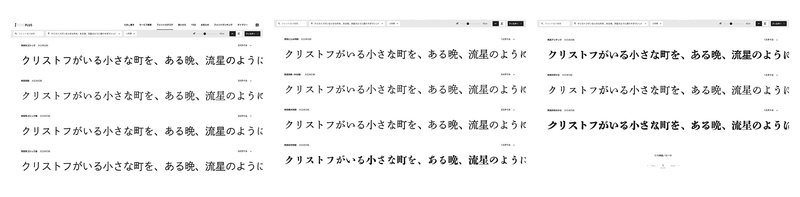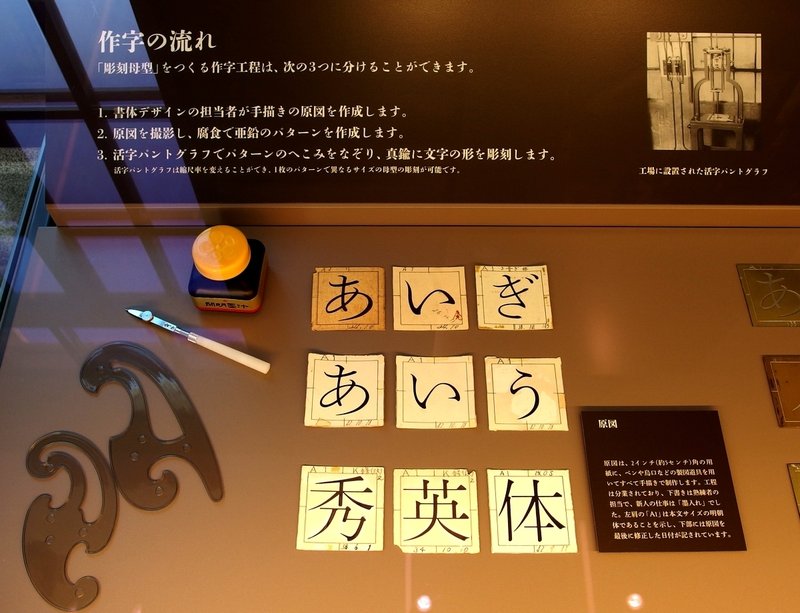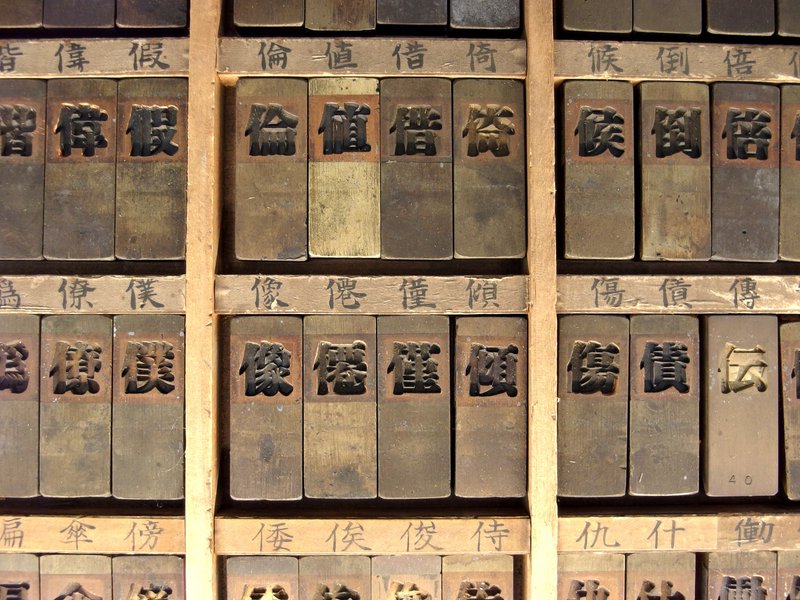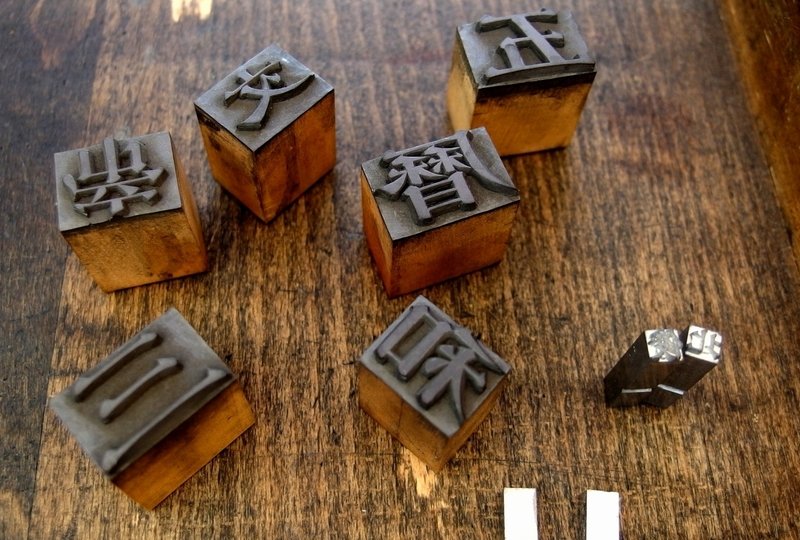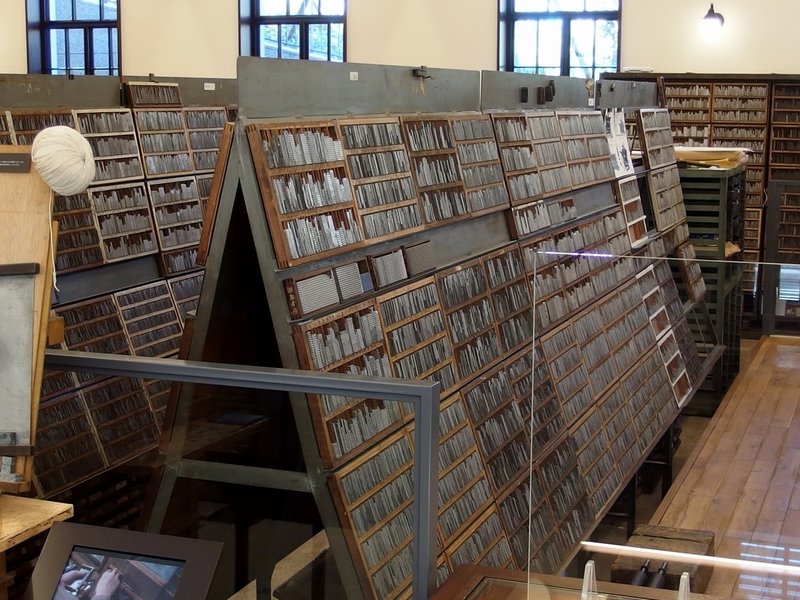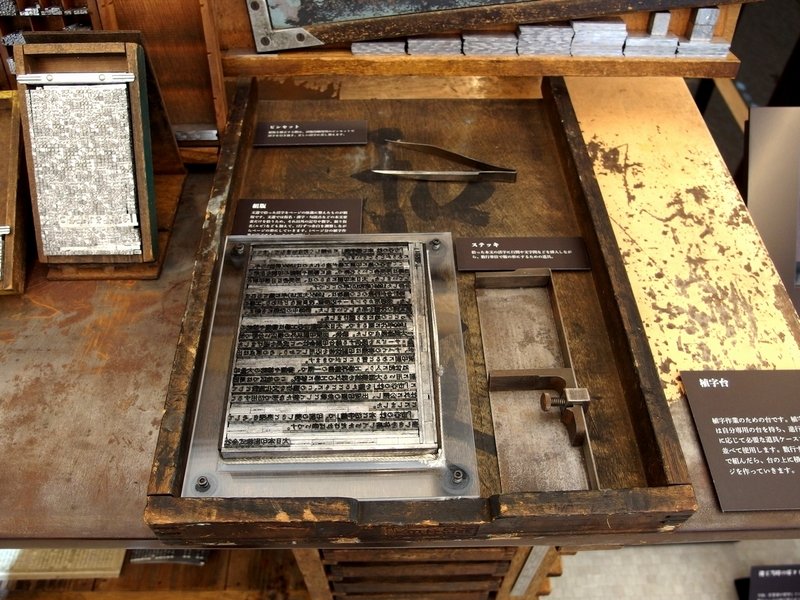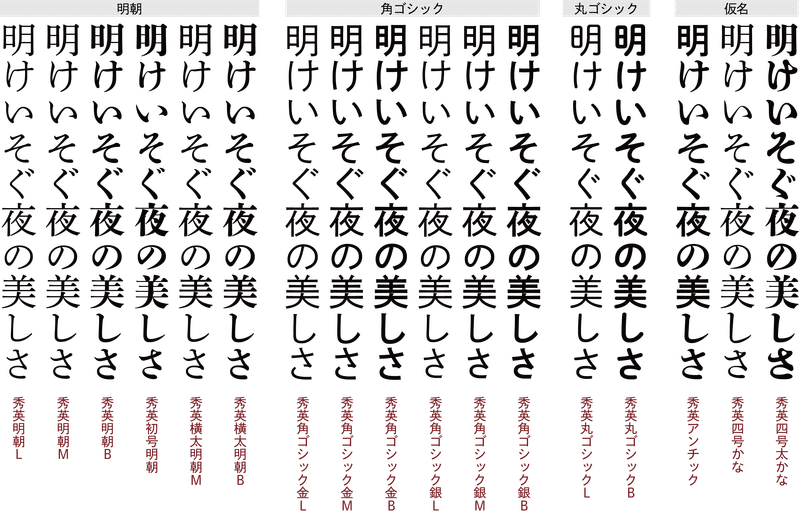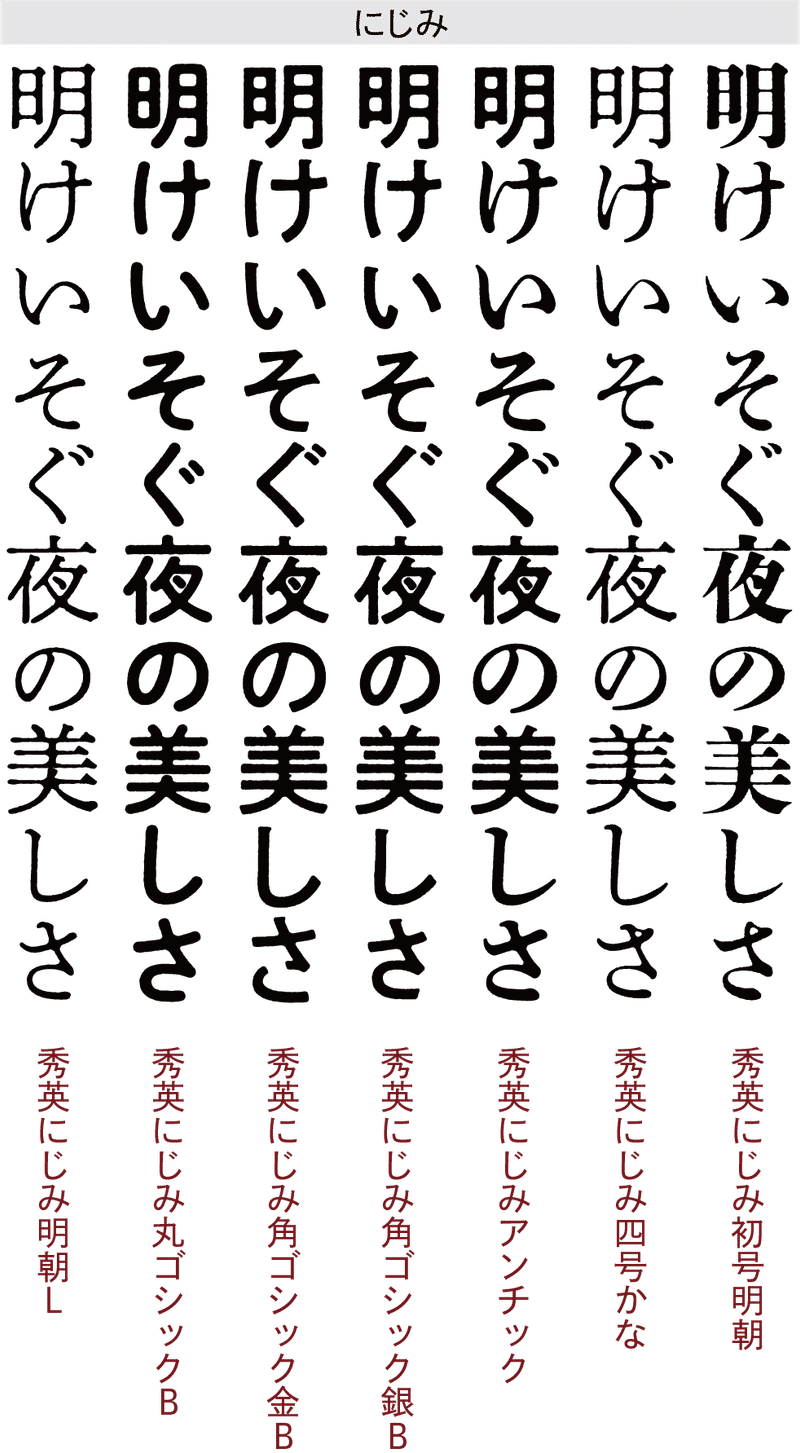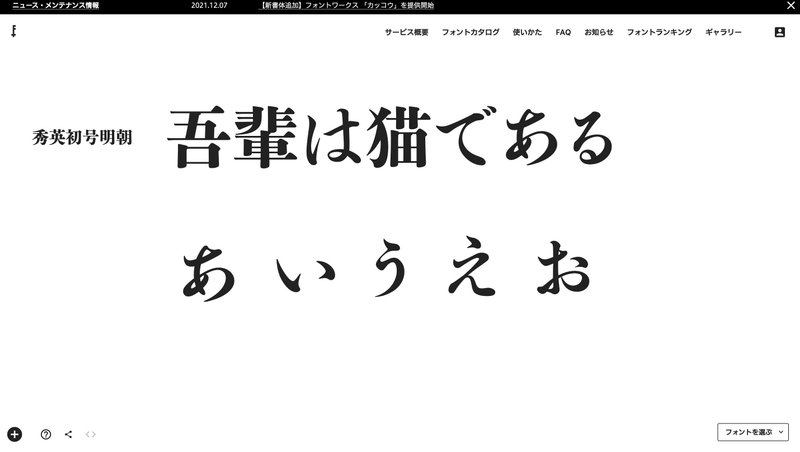
100年以上の歴史を持つ「秀英体」は大日本印刷(DNP)が開発したフォントだということ、ご存知でしたか? そして、DNPのルーツは明治9年創業の「秀英舎」にあります。
「大日本印刷(DNP)」とは
大日本印刷といえば、誰もが知っている、日本を代表する総合印刷会社です。読み方は「だいにほん」ではなく、「だいにっぽん」です。
社名の英語表記「Dai Nippon Printing Co., Ltd.」からDNP(ディー・エヌ・ピー)と呼ばれることも、最近は増えたような気がします。
現在DNPは、雑誌や書籍などの「紙の印刷」に限らず、印刷と情報(P&I:Printing & Information)の強みを基盤として、包装・建材・エレクトロニクス製品などのほか、エネルギー分野やライフサイエンス分野にも注力しています。
私たちが生活の中で使用しているクレジットカード、コンビニ等で手にするさまざまな製品のパッケージなど、DNPが製造しているものは少なくありません。
そんな印刷業界大手のDNPですが、創業は今から145年前にさかのぼります。「秀英舎」という会社です。皆さん、ご存知でしたか?
秀英舎は、明治維新後まもない1876年(明治9年)、東京・銀座の地で創業しました。「印刷を通じて人々の知識や文化の向上に貢献したい」という熱い想いが創業の原動力だったそうです。
明治初頭、欧米の思想や最先端の技術情報等を伝える上で重要な役割を果たしたのは書物でした。そして、その大量生産を可能にしたのが、当時日本に入ってきたばかりの「活版印刷」の技術だったのです。
1886年(明治19年)、秀英舎は東京・市谷に工場を建設します。1923年(大正12年)の関東大震災で銀座の本舎工場が焼失したため、本社機能を再開発工事が進んでいた市谷に移します。
そして、1935年(昭和10年)、秀英舎は日清印刷と合併し「大日本印刷」となります。
2015年、この地に、本社機能をもつ「DNP市谷加賀町ビル」が完成しました。
また、この一帯で武蔵野の雑木林をイメージした「市谷の杜」の開発を進めており、緑がとても豊かな場所になっています。年々、その緑の風景は広がっていると感じます。
以上、1世紀半に近いDNPの変遷を簡単にまとめてみました。
「秀英体」のルーツを探る
秀英体は、DNPが秀英舎の時代から100年以上にわたり開発を続けているDNPのオリジナル書体です。1912年(明治45年)には、見出し等に使う大きな活字「初号」から、ルビ等に使う小さい活字「八号」まで、各活字サイズの秀英体の明朝体が揃いました。
秀英体は、築地体と並んで「和文活字の二大潮流」と評され、新たに生まれた金属活字や写真植字の書体やデジタルフォントのデザインに、大きな影響を与えてきたと言われています。
秀英体は、“気骨のある初号” “流麗で繊細な三号” “明るく落ち着いた四号”と評されるように、活字の大きさに合わせてデザインされており、その骨格も異なっています。また、100年以上にわたり使われ続ける中で、印刷方式の変遷に合わせてアップデートを続けてきました。
「広辞苑」では、66年前の1955年(昭和30年)に刊行された初版から最新の第7版まで秀英体が使用されています。新潮文庫やベストセラー小説でも秀英体が多く使われており、書籍好きの方は必ず目にしてきた書体なのです。
創業130年を目前にした2005年に、秀英体のリニューアルプロジェクト「秀英体 平成の大改刻」がスタートします。約7年をかけて、本文用書体「秀英明朝ファミリー」・見出し用書体「秀英初号明朝」・新書体「秀英角ゴシック金/銀」「秀英丸ゴシック」の10書体を開発し、DTP環境や電子書籍ビューアーやワープロソフト等、オープンなデジタル環境に向けてのライセンス提供もスタートしました。
その後、2008年にはディスプレイ表示での視認性を考慮した「横太明朝」を開発、2015年には「四号かな」「四号太かな」「アンチック」のかな書体を復刻した他、2015年からは活版印刷の風合いを表現した「にじみシリーズ」の開発に取り組んでいます。
ながらくDNPのハウスフォントだった秀英体シリーズが、パソコンやDTPのデジタルフォントとして、また、デジタルサイネージやWebフォントとして広く使用できるようになったのは、わりと最近のことなのです。
秀英体の主要書体ラインアップ
秀英体の主要書体ラインアップ(にじみ)
それでは、秀英体の中で、フラグシップ的な存在の「秀英初号明朝」を、FONTPLUSで「ためし書き」してみましょう。
秀英初号明朝って、力強さの中にも、愛嬌を感じる書体ですよね。
この書体、明治時代に作成された金属活字の面影をきちんと復刻しているので独特の表情がありませんか? 特にひらがなの「あ」とか「え」とかは、ちょっと斜めというか、少し平行四辺形がかった感じがしませんか?
そんな個性ある見出し書体、好きです。
次に、FONTPLUSで現在使用できる秀英体の中で代表的な書体について、Webフォントのためし書きで確認してみましょう。
秀英ゴシック銀はとても印象的な書体ですね。ゴシック体なのに筆で書いたような優しい味わいを感じます。
金属活字を紙に押し付けた時の「インクのにじみ」を、コンピューター処理で精緻に再現した秀英体の「にじみシリーズ」のうち、FONTPLUSでは「秀英にじみ明朝L」が利用できます。
活字と本づくりに関する文化施設「市谷の杜 本と活字館」
2021年2月にDNPがオープンした、活字と本づくりに関する文化施設「市谷の杜 本と活字館」で、「秀英体」をテーマにした企画展「秀英体111 秀英体ってどんな形?」が開催(2022年2月27日まで)されているので行ってきました。(入館は予約制)
この「市谷の杜 本と活字館」は、1926年(大正15年)に建てられた旧営業所棟を創建当時の姿に修復・復元した建物で、DNPの祖業である活版印刷の工場を一部再現しています。活字や活版印刷の歴史だけでなく、レトロな建物も印象的でした。
以前からあった「時計台」の文字盤も古い写真から竣工当時のデザインに復元されたそうで感激しました。この記事のメインビジュアルの写真は、昨年2020年11月に完成した時の「市谷の杜 本と活字館」です。時計も写っていますよね。
1階は、「活字がどのようにして作られ、どのように印刷・製本されるのか」が理解できる活字歴史館という感じです。設備の実物や解説の動画を見ながら、誰でも楽しめる常設展示です。高校生や大学生の皆さんは、ぜひ、見学してほしいです。親子で訪問するのも良いですね。
コミュニケーションの基盤として、なくてはならない重要な役割を果たしている文字やフォント。それらの歴史や仕組みを知ることは大切だと思うのです。そして、それらを知ることで文字が楽しくなり、どう活用するかといった知恵やヒントがたくさん発見できます。
秀英体の原字
活字母型(金属活字の金型)
活字
活字棚
植字台(活字組版)
DNP 感情表現フォントシステム
DNPの秀英体開発部門では、書体の開発にとどまらず、書体に関連したコミュニケーションツールも開発しています。その一つのソリューション「DNP感情表現フォントシステム」をご紹介します。
テキストの内容に応じて、その感情にマッチしたフォントに自動で変換して表現するシステムです。例えば、楽しい内容は丸みのある書体、怒っている内容はトゲトゲした書体、「和」のイメージは筆書体で表示します。この仕組みを発展させて、映像に含まれる音声の内容に合わせて、自動的に適切なフォントがあたったテロップで表示することも可能にしていました。フォントが持つ役割を活用することで、テロップや字幕放送の表現を彩り、耳が不自由な方にとって、あるいは屋外サイネージや車内広告といった音声が出せない環境において、人と人とのコミュニケーションをより豊かにするツールとして活躍しそうです。
日頃あまり意識することはないけれど、コミュニケーションを支えるなくてはならない基盤――。
そんなフォントは、私たちの情報革命にとって、隠れた主人公なのかもしれませんね。